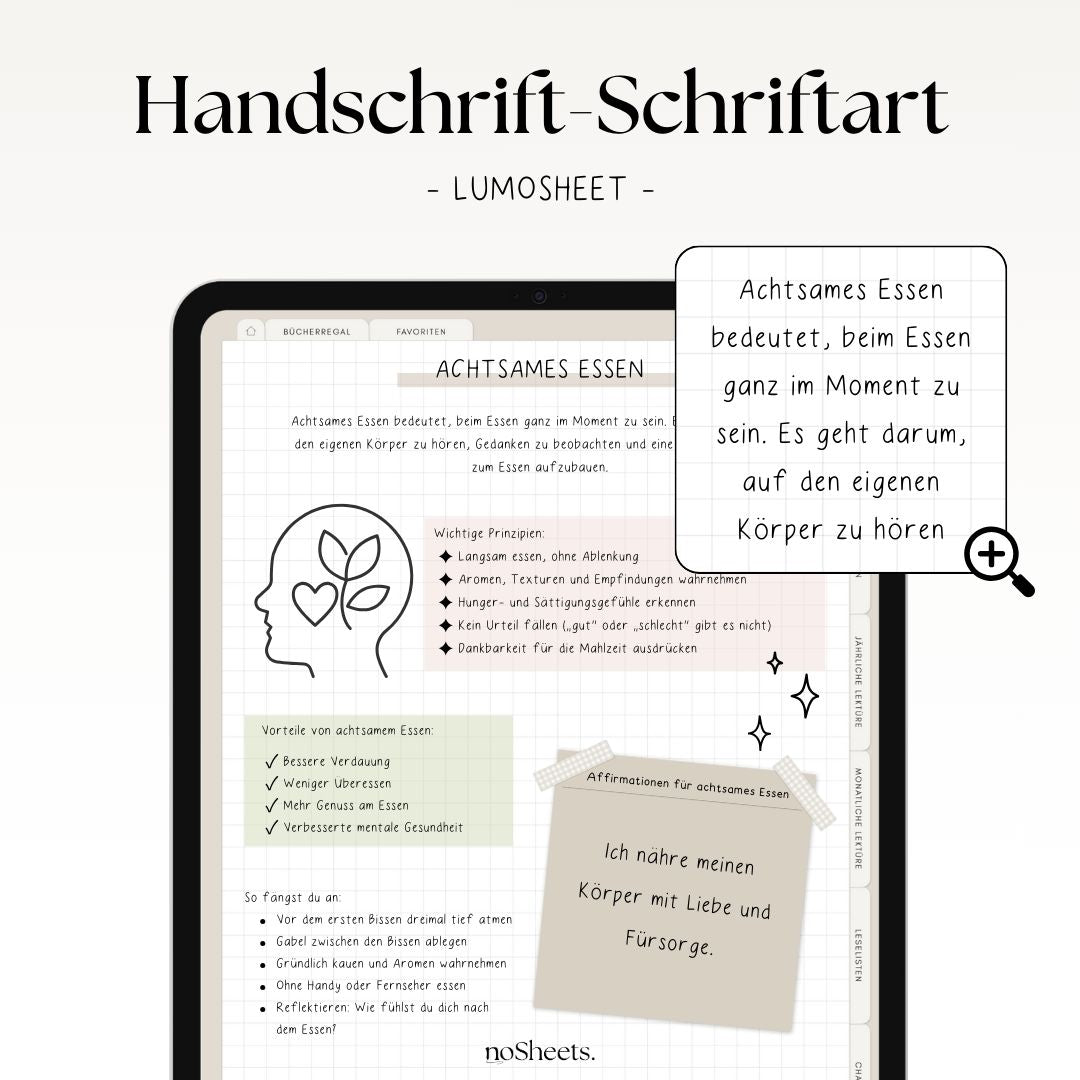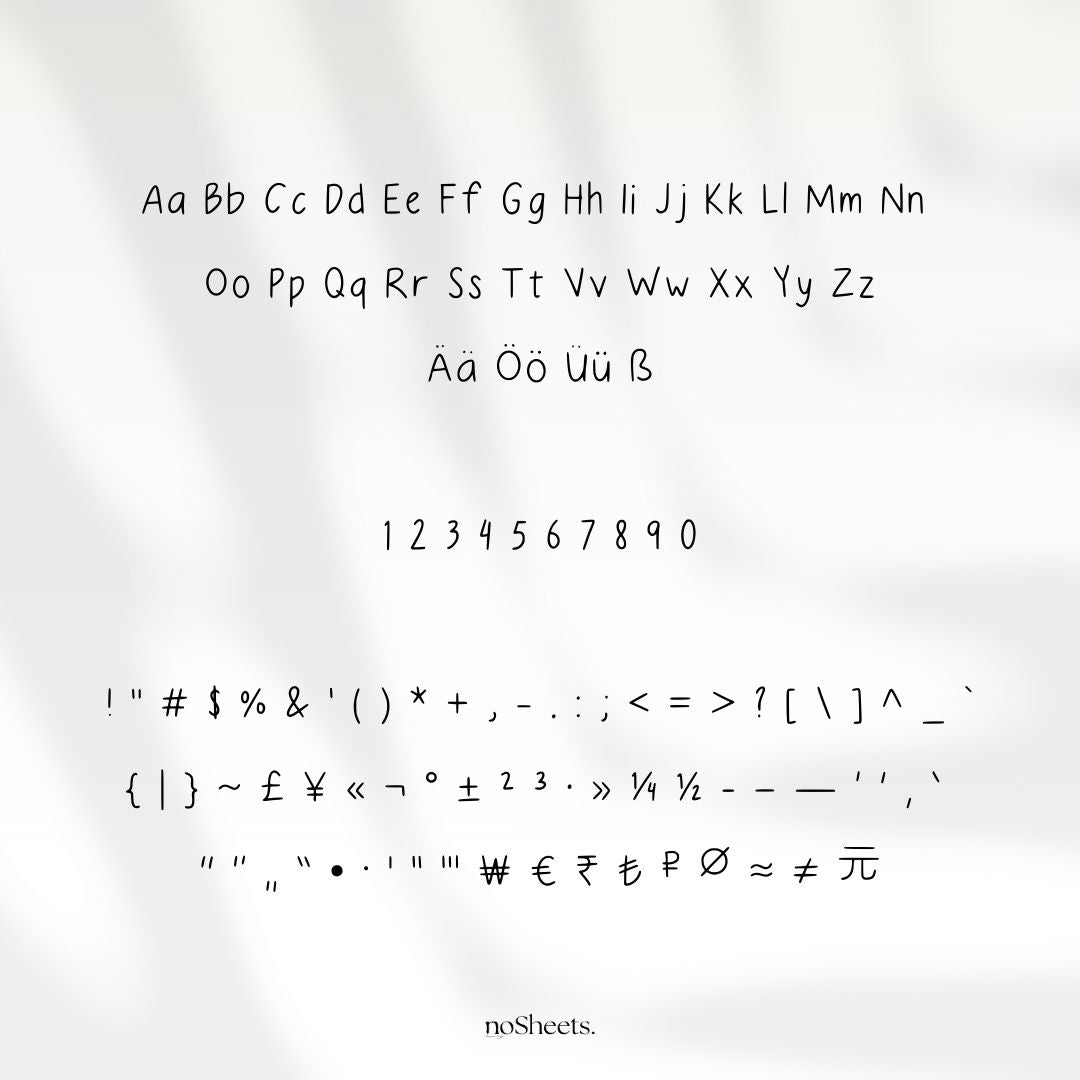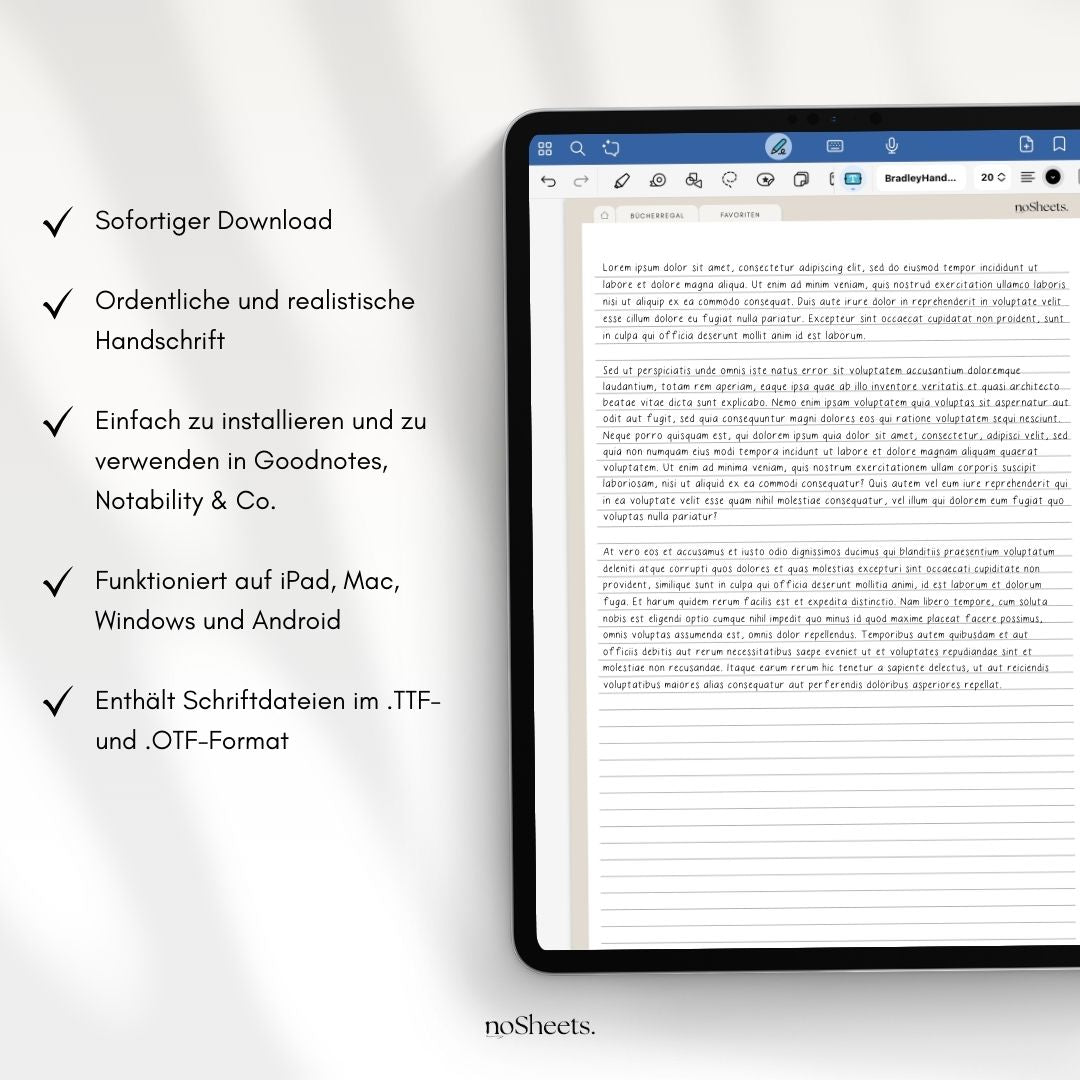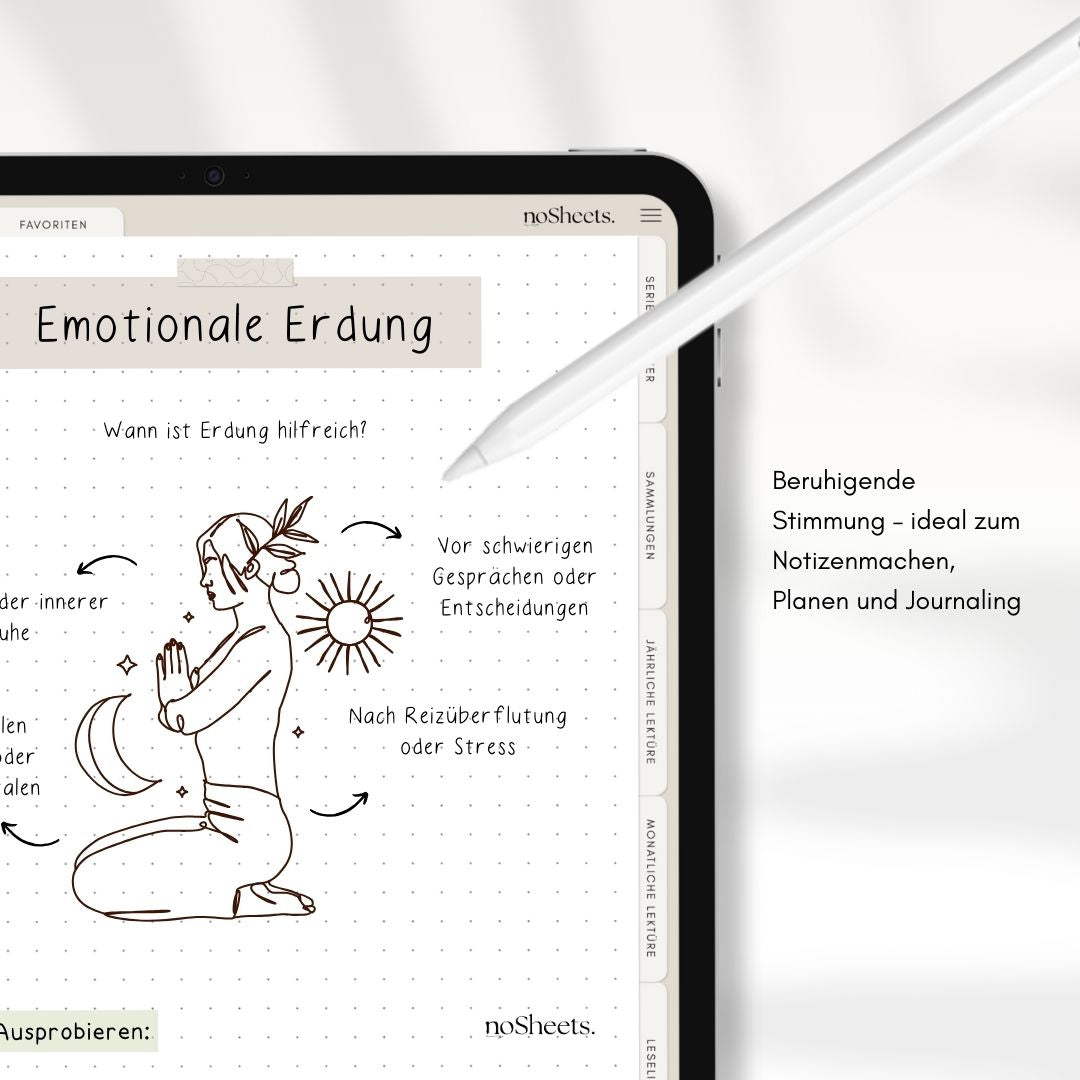
Font | Lumosheet
Lumosheet – Dein Text im strahlenden Licht
Leuchtend. Klar. Frisch.
Lumosheet bringt deine Worte zum Glänzen – mit einem elegant hellen Erscheinungsbild, das sowohl Aufhellung als auch frische Ästhetik vermittelt.
✓ Hell & minimalistisch
Feine Linien und helle Tönung sorgen für eine sanfte Eleganz, die auf jedem digitalen Hintergrund auffällt – ideal, um Inhalte leicht und klar zu gestalten.
✓ Modern & zurückhaltend
Lumosheet ist puristisch und wirkungsvoll. Selbst mit minimalistischer Anmutung bewahrt die Schrift ihre Wärme – ideal für reduzierte, ästhetische Designs.
✓ Digital-Ready
Bewährt in Apps wie GoodNotes und Notability – Lumosheet lässt sich mühelos digital einsetzen und bewahrt dabei seinen klaren, modernen Charakter.
Perfekt für…
✓ Digitale Planer und Scrapbooks
✓ Handgeschriebene Titel & Anmerkungen
✓ Persönliche Designs: Einladungen, Grüße, Social Media